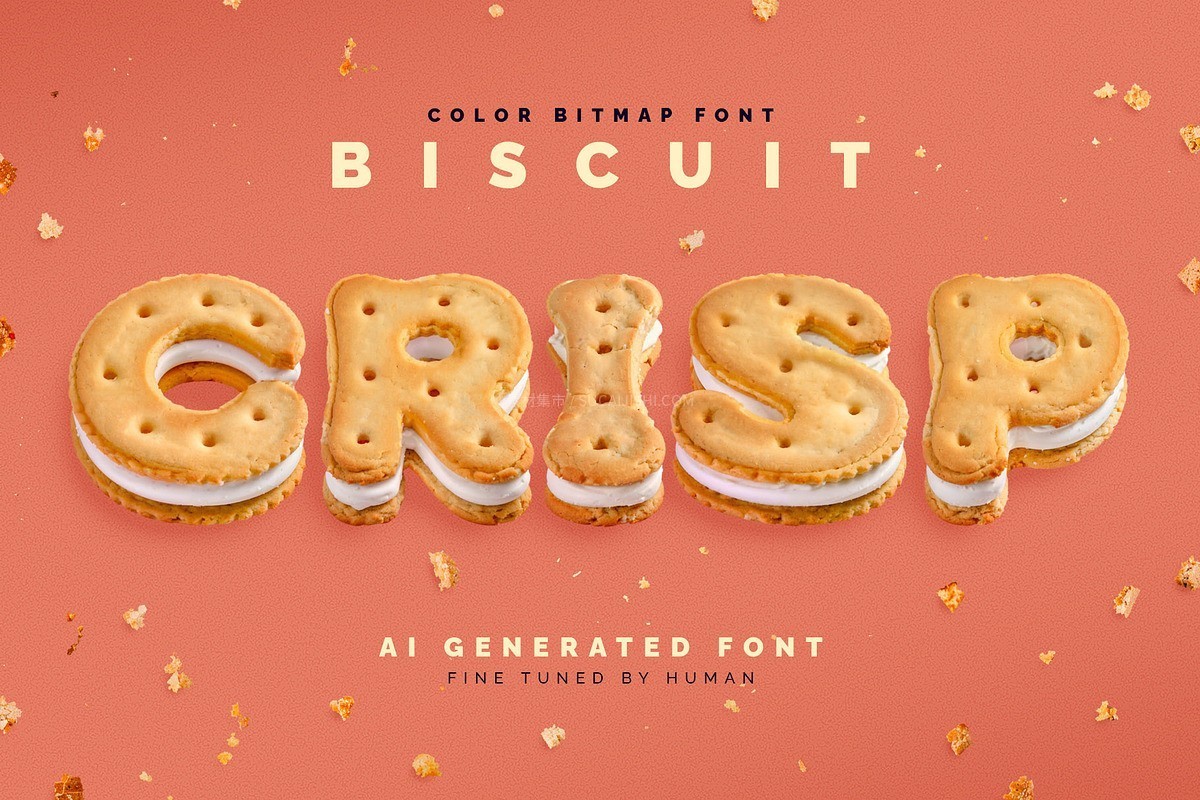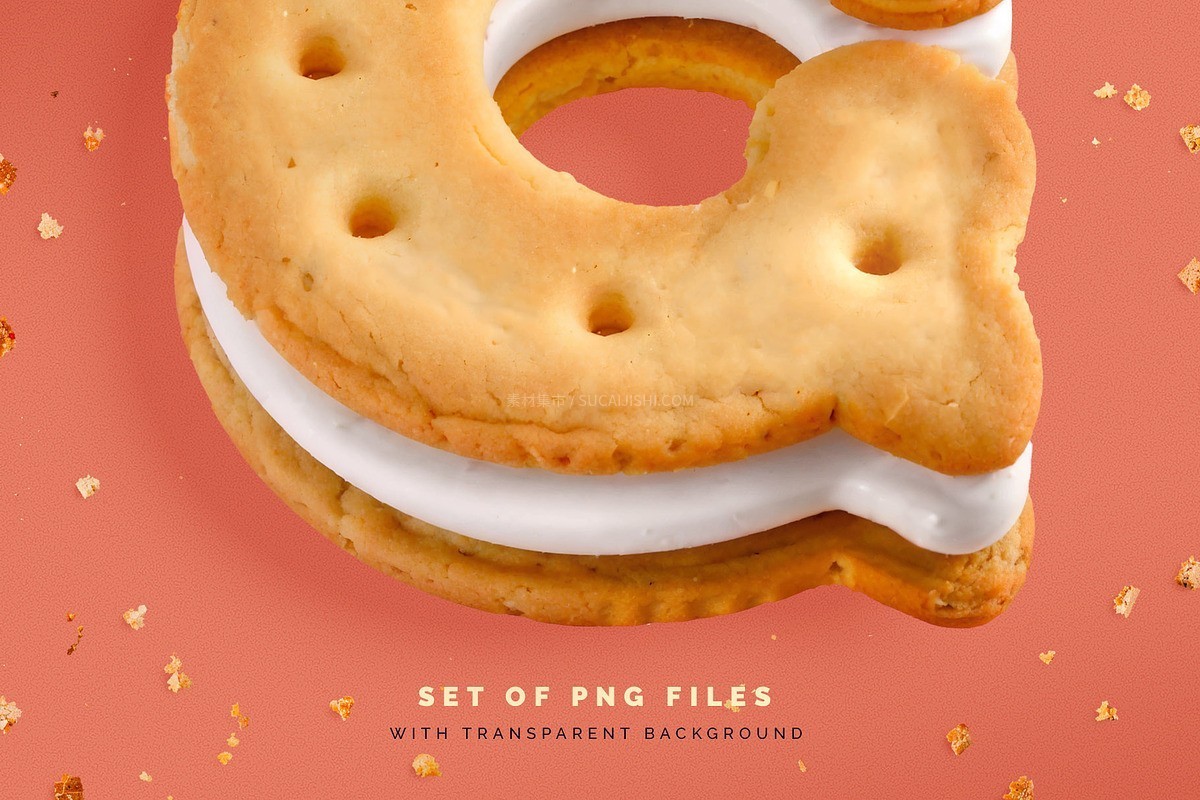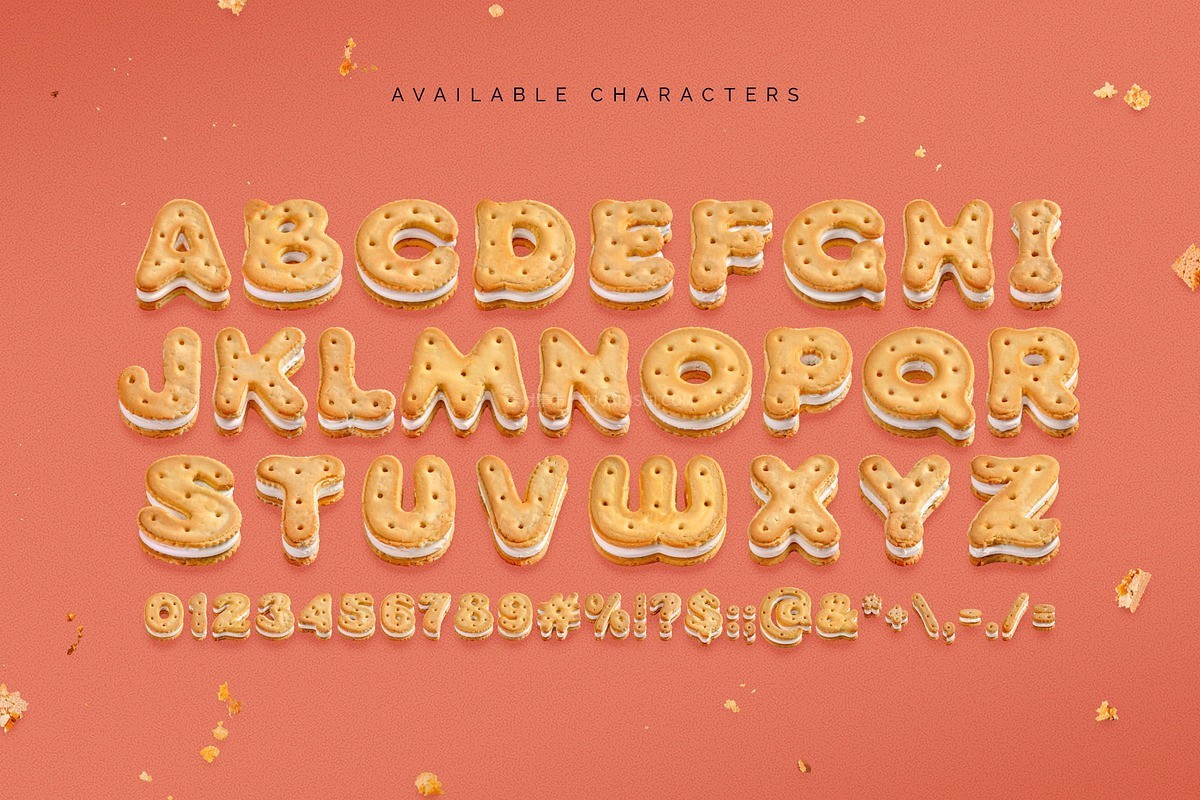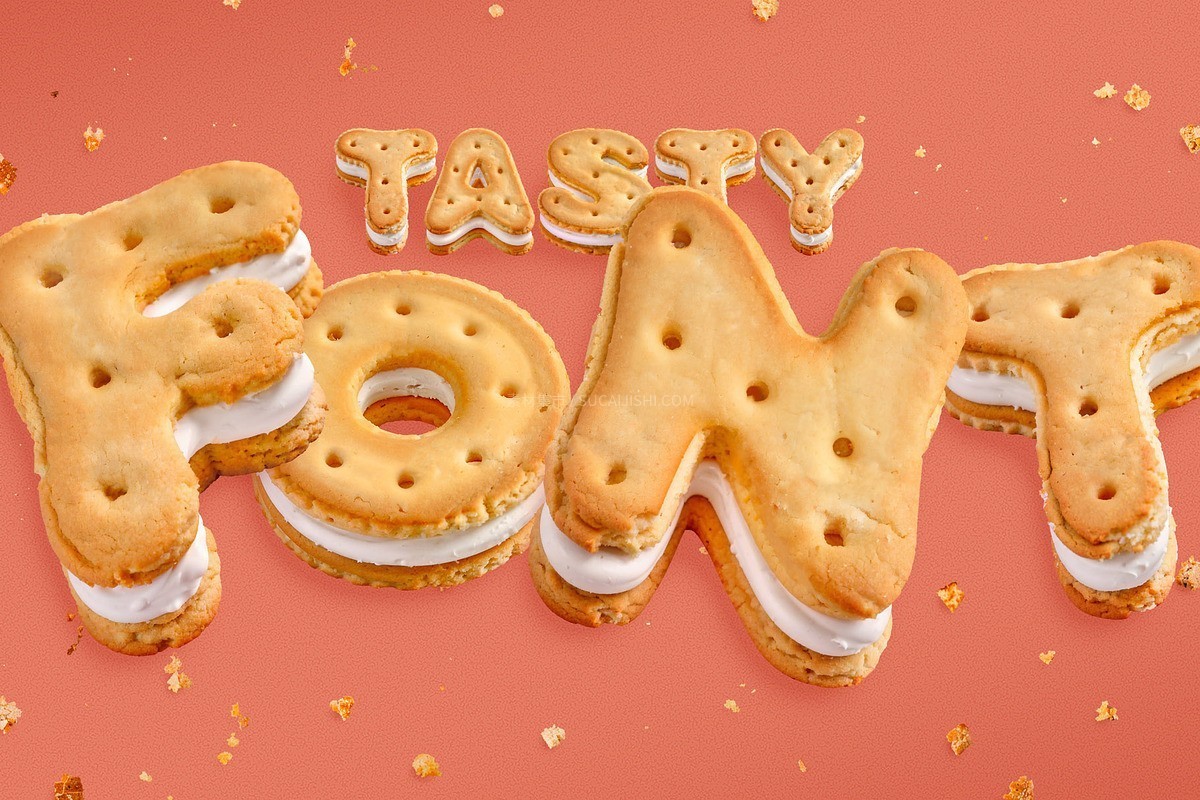
Biscuit Crisp 酥脆夹心饼干彩色位图字体
这款字体采用尖端生成式人工智能技术创作并经过人工精细调整,字母形状如同逼真的酥脆夹心饼干,呈现出高度人性化的视觉效果。作为一款彩色位图 OpenType-SVG 字体,它的使用方法与标准 OTF 字体一样便捷。此外,素材包还额外包含带有透明背景的全分辨率 PNG 文件(平均分辨率为 1500x1500 像素)。注:该字体仅支持英文和基本标点符号,具体可用字符请参考预览图。